간판 역사 100년, 진귀하고 흥미로운 이야기_1.근대 간판디자인
<간판 역사 100년전>이 근현대디자인박물관 개관 4주년 기념 특별전으로 기획되어 선보였다. 전시는 크게 다섯 부분으로 나뉘어져 한 달간 진행되었다. 제 1파트에서는 60여장의 사진 속에 나타난 초기 간판의 모습을, 제 2파트에서는 일제강점기부터 현대에 이르기까지 박물관에서 소장하고 있었던 실제 간판 약 170여종이 전시되었다. 제 3파트에서는 서울의 대표 거리 다섯 곳의 거리 간판 풍경전을, 제 4파트에서는 전문디자이너들이 참여한 10대 도시 간판디자인 초대전이 펼쳐졌다. 1960년대 거리를 재현해 기념사진을 촬영할 수 있도록 꾸며지기도 했다. 전시는 마무리되었지만, 박물관 측 협조로 폰트클럽에 전시 내용 중 일부를 소개한다.
한국 간판의 시초는 술과 주막이 등장했던 삼국시대 또는 천하대장군(이정표 기능)이 생겨난 고려시대로 추정된다. 문헌상의 기록으로 고려도경 제3권 방시(坊市)에 고려개경의 시전(시장)에 대한 기록에서 찾아볼 수 있다. 광화문에서 남쪽 대로를 따라 행랑 건물로 조성되어 있어 이러한 상업용 건물에 상호를 나타내는 방(榜)이 방문에 붙어 있었다는 기록이 그것이다. 방의 사전적 의미는 ‘걸다, 게시하다’는 의미로 오늘날 간판이라는 의미로 사용되었음을 짐작할 수 있다. 초기 조선시대에는 일종의 주렴에 해당하는 포럼을 출입문에 드리워 주막을 표시하였고, 또 추녀 끝에 등롱을 매달고 거기에 ‘주(酒)’자를 써넣어 간판을 대신하였다. 즉, 주막이나 객주집 문 앞에 기둥을 세워 그 위에 남포등을 고정시킨 장명등을 설치하여 거기에 ‘주’자나 옥호를 써넣고, 밤이면 불을 켜서 영업용 간판으로 삼았던 것이다.
광복이전(1900년대 초~1945년)의 간판디자인
일제강점기로 접어들면서 일본 간판 문화가 이입되었다. 이때 ‘간판’이라는 용어부터 시작해 다양한 형태의 간판이 들어왔다. 기관, 단체는 물론 상점, 회사 등이 붓글씨로 된 입간판을 사용하기 시작하였다. 큰 간판의 기원 역시 일제시대로부터 시작된다. 조선말기 상점은 주로 간판을 걸지 않았는데, 이것은 자신이 파는 물건이 그대로 간판이 되었고, 또 시장을 통해서 물물교환을 하던 시기의 특성이기도 하다. 그 후 1910년대에 서울 번화가나 각 지역 본전통에서 급격히 늘어난 상점들의 간판은 크기가 상점에 비해 크고 과시적이다. 1920년대부터 일본을 통하여 네온사인이 등장하였으나 규모도 적고 색채도 단조로운 것이었으며 널리 보급되지는 못했다. 입간판은 1930년대부터 널리 보급되었다.
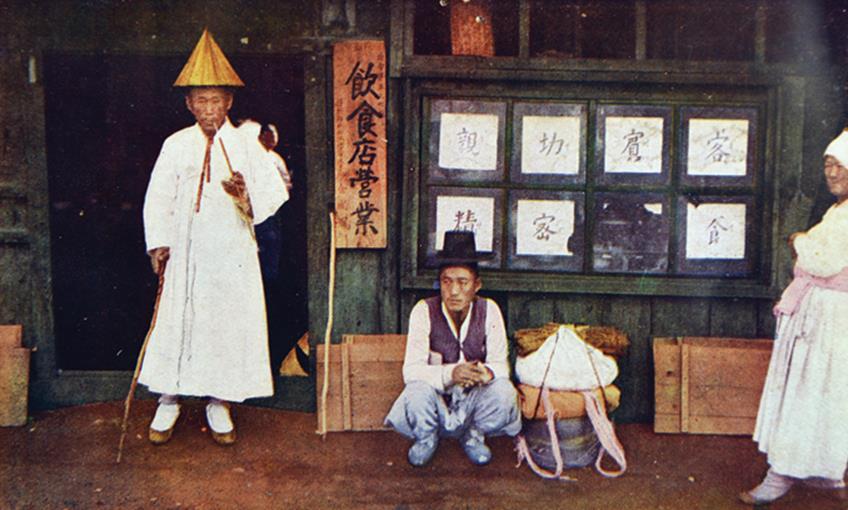
음식점 간판
1910년경 | 엽서 | 6.8×12.5cm
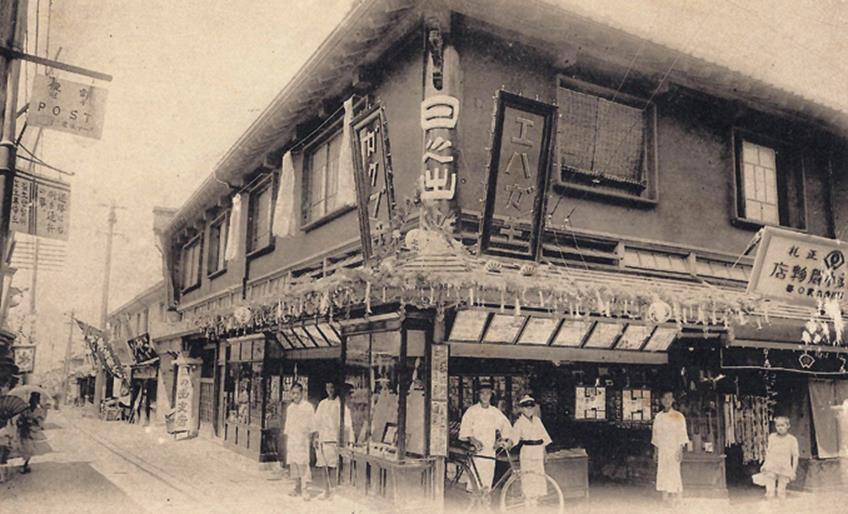
1920년대 명동의 모습
1920년대 | 엽서 | 14.2×9.0cm
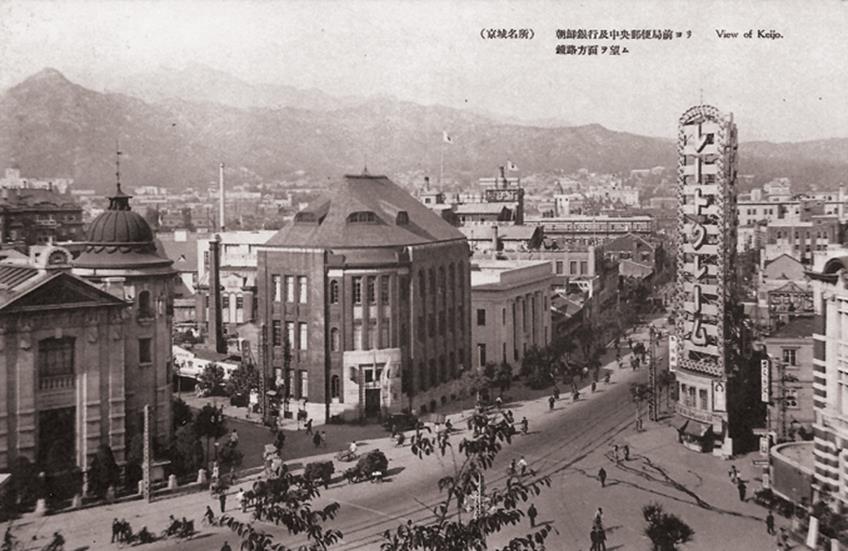
경성은행 앞 거리의 모습
1920년경 | 엽서 | 14.2×9.0cm
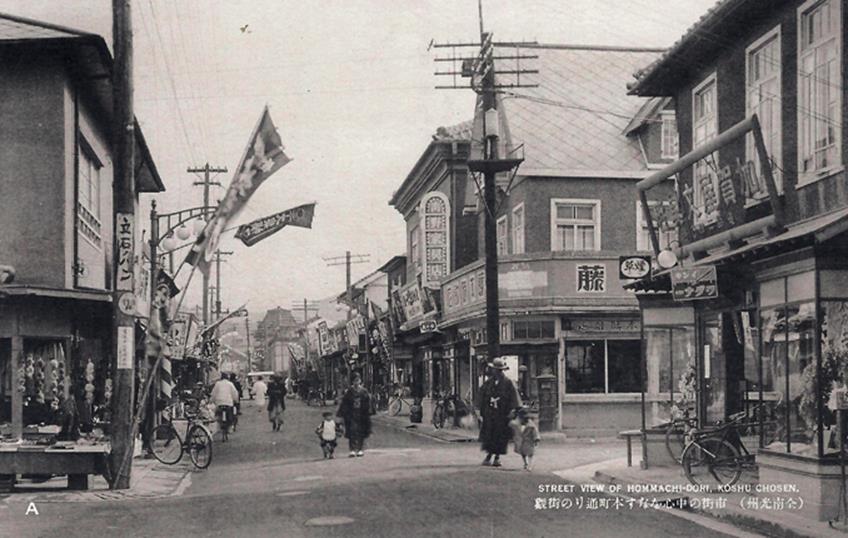
광주 본전통 거리
1920년대 | 엽서 | 14.2×9.0cm
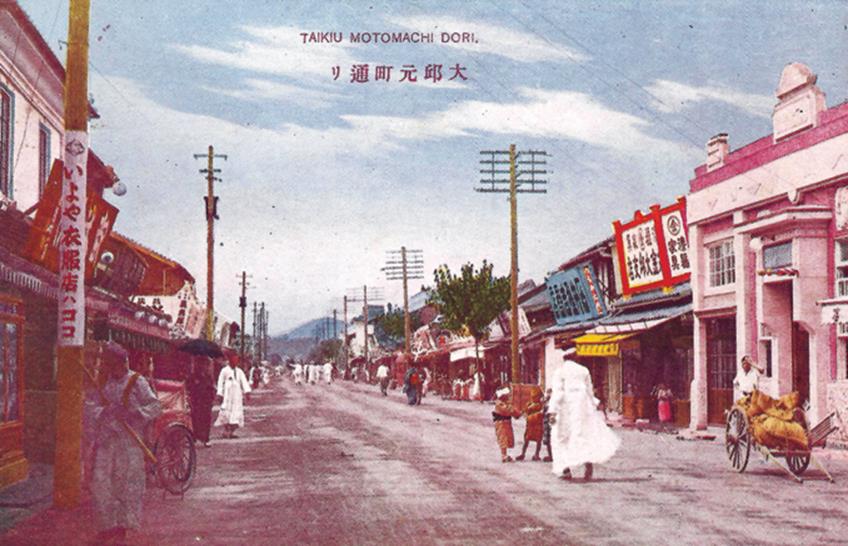
대구 원정통 거리
1920년대 | 엽서 | 14.2×9.0cm
부산 장수통 거리
1920년대 | 엽서 | 14.2×9.0cm
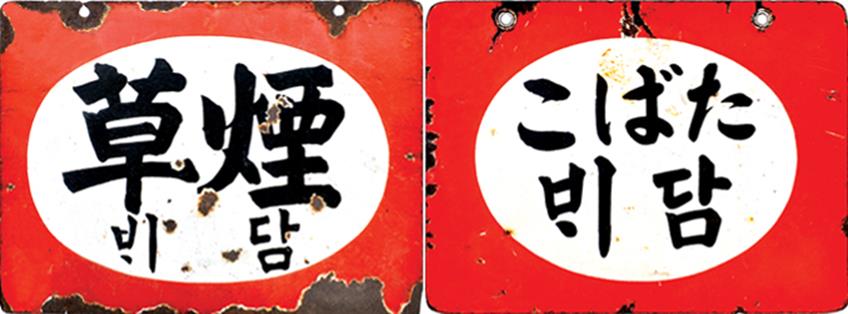
담배 간판 1920년대 | 법랑 | 30×22.2cm
담배 간판 1920년대 | 법랑 | 45.1×33.1cm
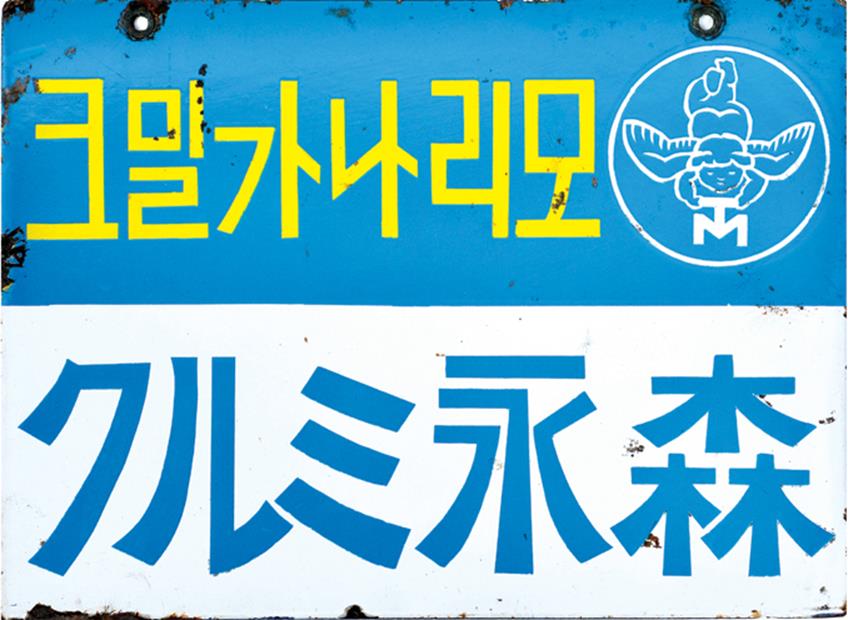
모리나가우유 간판 1930년대 | 법랑 | 45.3×33.1cm
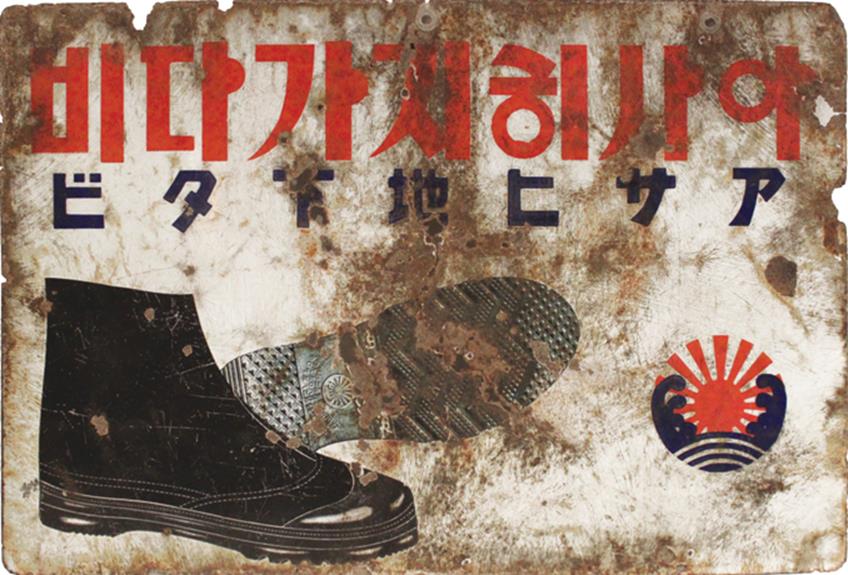
아사히지가다비 신발 간판 1930년대 | 법랑 | 45.2×30.6cm
술 간판 1910년대 | 법랑 | 36×30cm
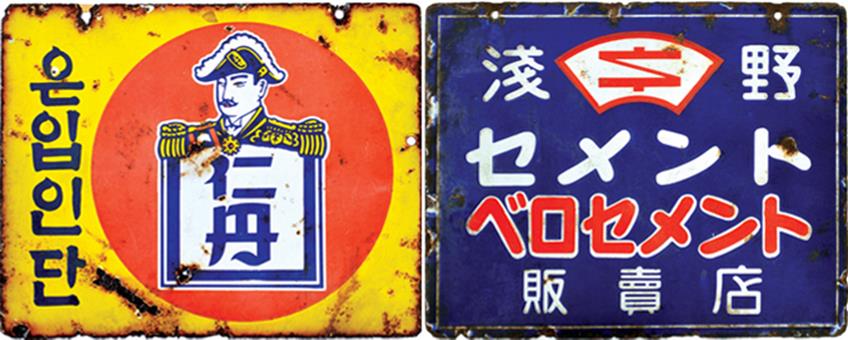
인단 간판 1920년대 | 법랑 | 45.2×36cm
베로세멘트 판매점 간판 1930년대 | 법랑 | 45×36cm
자동차영업소 간판 1920년대 | 목재 | 42×29cm
나시요나루 건전지 간판 1920년대 | 법랑 | 45.2×30cm
광복이후(1945년대~2000년)의 간판디자인
광복 이후 표현 양식에 많은 시도와 시행착오를 거치면서 정부정책의 일환으로 한글 전용 사용운동이 펼쳐졌다. 그러면서 ‘일본식간판 일소운동’이 일어나기도 했다. 1960년대 산업화와 도시팽창을 거치면서 1967년에는 네온사인 규제 해제 후 네온탑과 옥상간판이 성행하였고, 1970년대에는 강철 간판들이 플라스틱 재료로 대치되기 시작하였다. 물론, 약국과 병원이나 큰 가게들은 이미 아크릴 간판이 걸었지만 작은 구멍가게도 플라스틱 재료를 쓴 것이다. 간판의 틀은 여전히 나무였지만 비닐을 씌우고 그 위에 글씨가 볼록하게 튀어 나오도록 붙여지기도 했다.
인동연탄 1980년대경 | 철재 | 61×44.8cm
국자표 미풍 1970년대 | 철재 | 34.8×24.5cm
소금 1970년대 | 철재 | 45×36cm
샘표간장연료 1980년대경 | 철재 | 61×44.8cm
우표, 수입인지 1970년대 | 법랑 | 45×35cm
승차권판매소 1970년대 추정ㅣ철재ㅣ43.5×60.5cm
샤니케익 1970년대 추정, 1970년대 | 법랑 | 39×16.6cm, 20×7cm
로켓트 전지 1980년대 | 철재 | 35.6×50.6cm
아모레 1970년대 추정 | 철재 | 39.8×79.5cm
이발 1980년대 | 철재 | 35.6×50.6cm
안남애향청년회 현판 1960년대 추정 l 목재ㅣ28×160×2cm
회곡 정미소 현판 1970년대 추정 | 목재ㅣ28×120×2.5cm